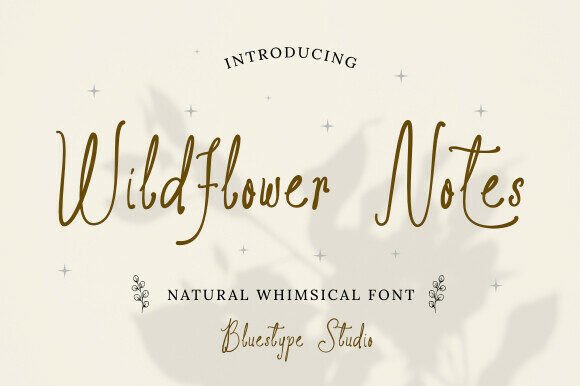
Wildflower Notes
์ •๋ฐ€ํ•˜๊ฒŒ ์ œ์ž‘๋œ Wildflower Notes๋Š” ๊น”๋”ํ•œ ๋ฒกํ„ฐ, ๋ถ€๋“œ๋Ÿฌ์šด ํƒ€์ดํฌ๊ทธ๋ž˜ํ”ผ ๋ฐ ์•ˆ์‹ฌํ•  ์ˆ˜ ์žˆ๋Š” ์ƒ์—…์šฉ ๋ผ์ด์„ ์Šค๋ฅผ ์ œ๊ณตํ•ฉ๋‹ˆ๋‹ค.
POD(์ฃผ๋ฌธํ˜• ์ธ์‡„) ์ œํ’ˆ, ๊ฒฐํ˜ผ์‹ ์ดˆ๋Œ€์žฅ ๋˜๋Š” ์†Œ์…œ ๋ฏธ๋””์–ด ๊ทธ๋ž˜ํ”ฝ์„ ๋งŒ๋“ค ๋•Œ Wildflower Notes๋Š” ์ด์ƒ์ ์ธ ์„ ํƒ์ž…๋‹ˆ๋‹ค.